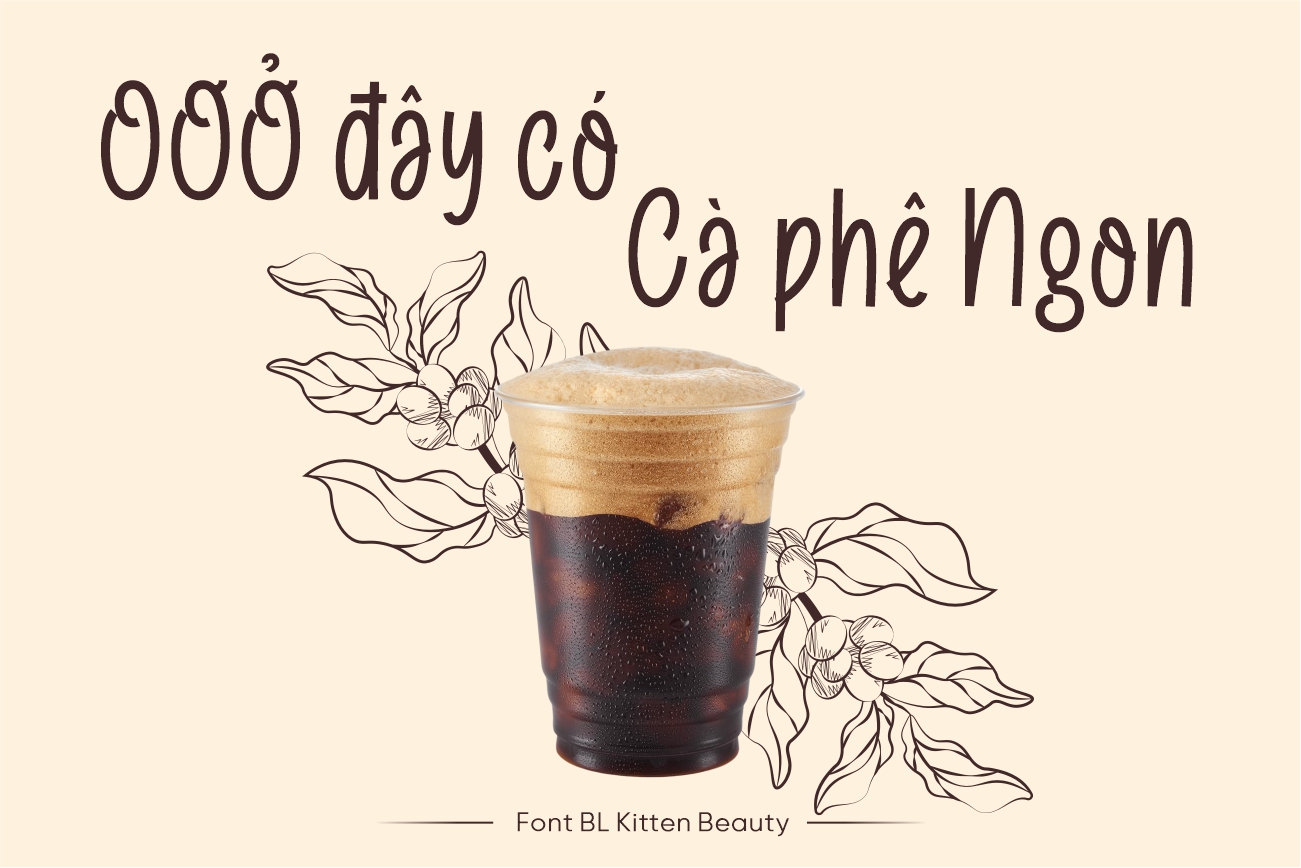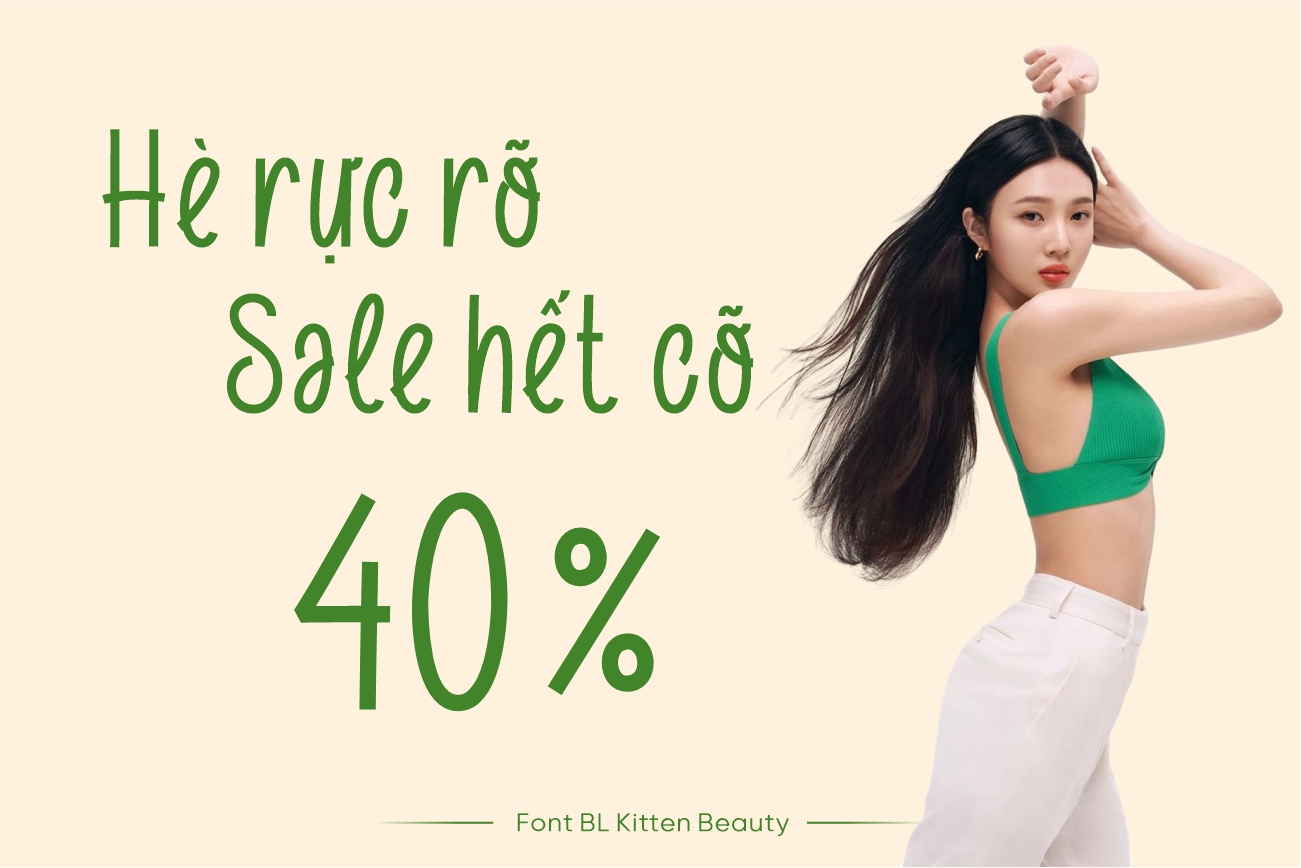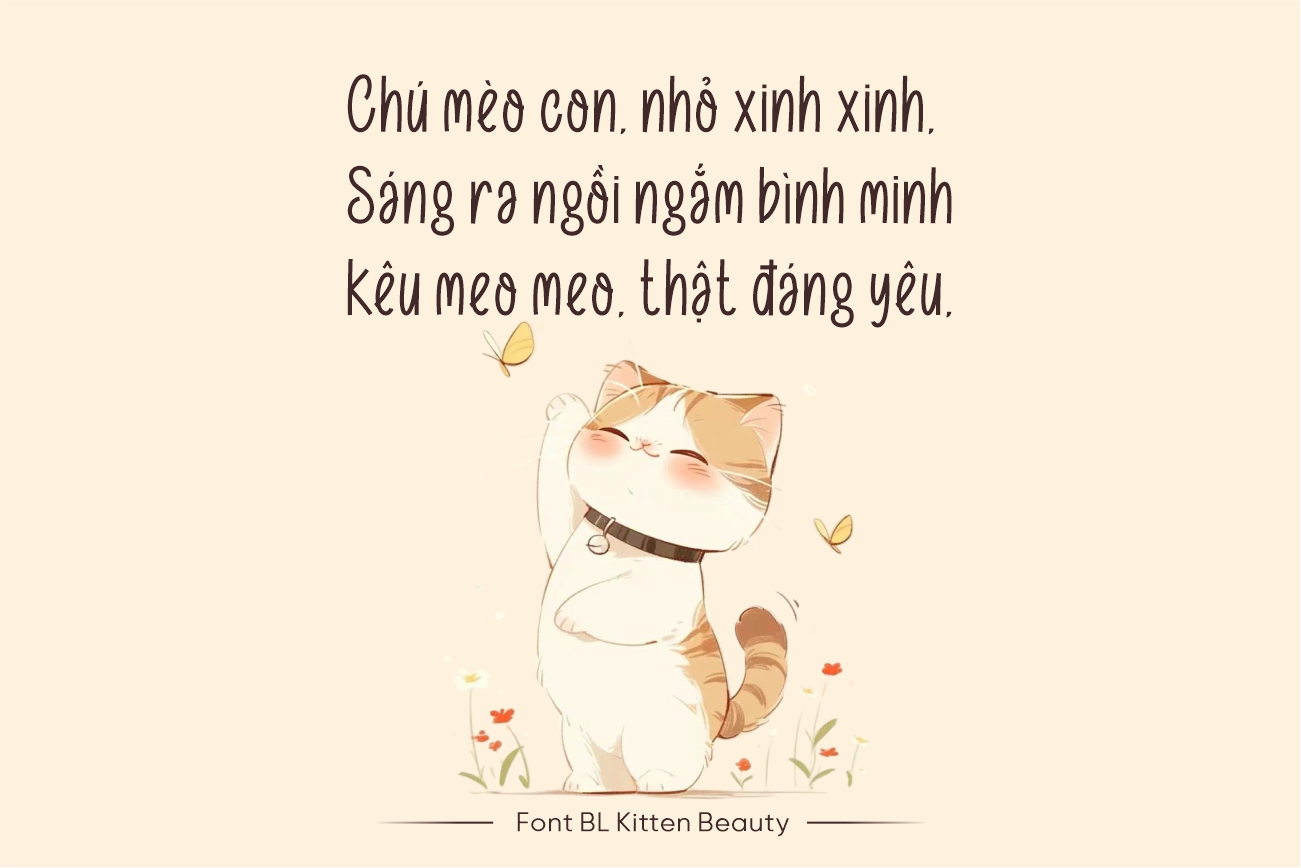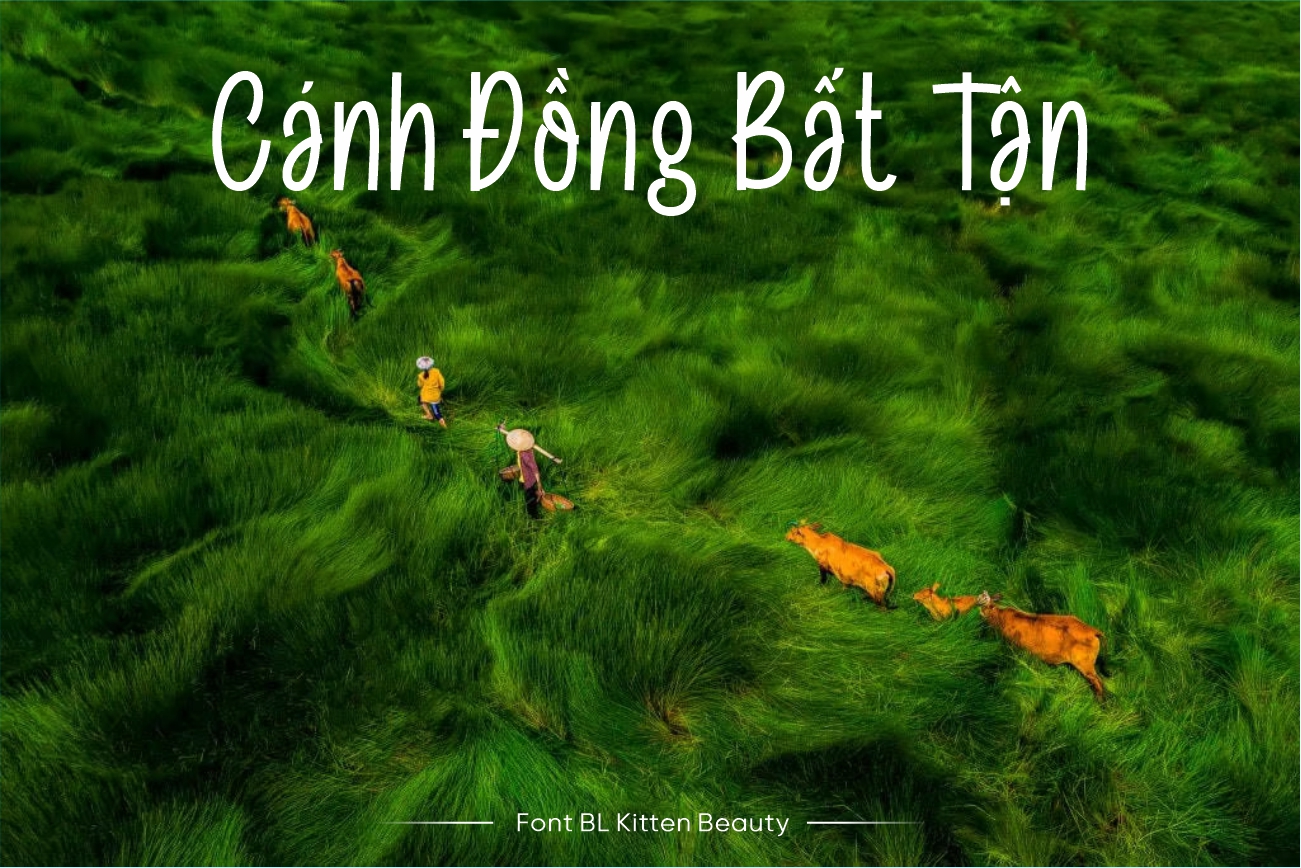
BL Kitten Beauty
Font Kitten Beauty Sans Serif mang phong cách thanh lịch, hiện đại và tối giản
🔹 Đặc điểm nổi bật:
Nét chữ gọn gàng, không chân, dễ nhìn trên cả màn hình và ấn phẩm in.
Giữ sự tinh tế và mềm mại trong từng đường nét, không quá cứng nhắc như nhiều sans serif truyền thống.
Có thể kết hợp trực tiếp với Kitten Beauty script để tạo điểm nhấn hài hòa: script dùng cho tiêu đề, sans serif dùng cho tagline hoặc nội dung.
Thích hợp với nhiều phong cách thiết kế từ thời trang, mỹ phẩm, wedding, lifestyle cho đến branding chuyên nghiệp.
💡 Ứng dụng thực tế:
Logo và nhận diện thương hiệu: tạo sự cân bằng giữa sang trọng và thân thiện.
Thiệp cưới, thiệp mời sự kiện: dùng sans serif làm text chính, kết hợp script cho tiêu đề lãng mạn.
Ấn phẩm truyền thông, poster, social media: đảm bảo dễ đọc mà vẫn giữ được nét thời thượng.